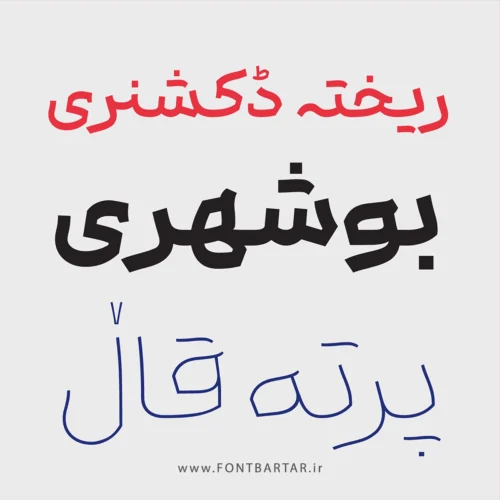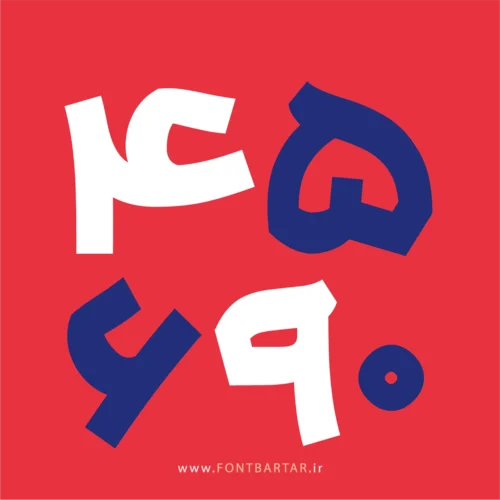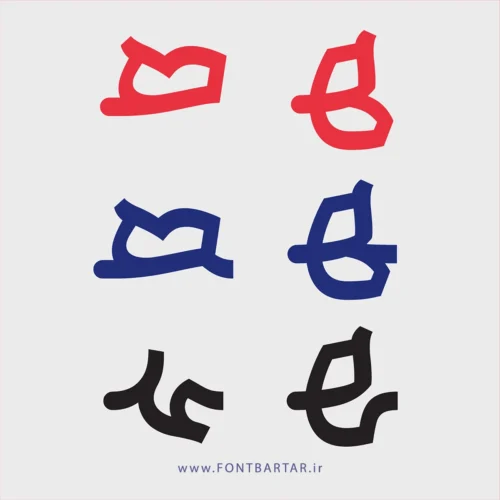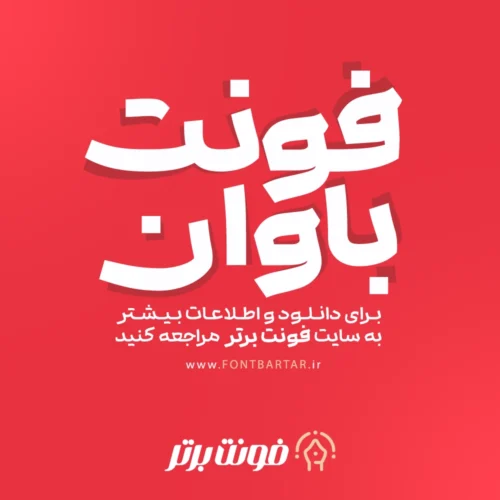
دانلود فونت باوان
فونت باوان با ترکیب ساختاری هندسی و ویژگیهای سنتی خط نسخ و کمی ثلث را دارد. چهره ای آشنا دارد و به آسانی ارتباط برقرار میکند. دانلود فونت تایپ گزینهای مناسب برای استفاده در تبلیغات، پستها و استوریهای شبکههای اجتماعی و همچنین بستهبندی محصولات مختلف تبدیل میکند.
فونت تایپ فارسی باوان در دسته فونتهای مونولاین (تک ضخامتی) قرار دارد، فونت تایپی باوان جوان و پر انرژی بوده و میتواند بهخوبی در متون کوتاه و نیمه بلند ایفای نقش کند.
- زبانهای پشتیبانی شده: فارسی , اُردو , عربی , کوردی
- اعداد فارسی: دارد